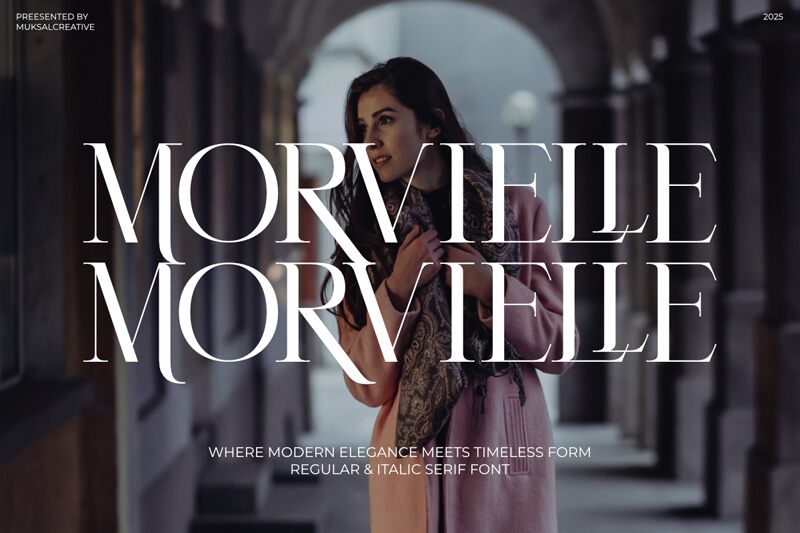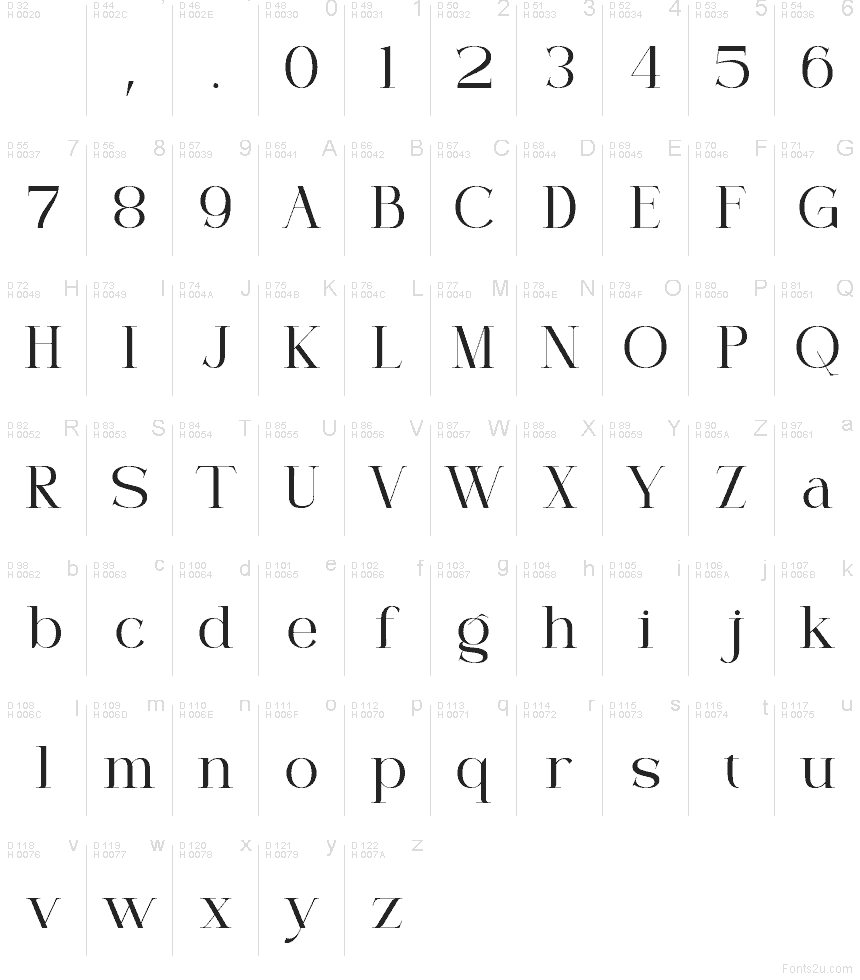
Morvielle Regular
Morvielle od Muksal Creative je bezplatné patkové písmo s vysokým kontrastem, jehož výrazná svislá osa a tenké spoje vytvářejí elegantní, módně laděný rytmus. Široké hlavní tahy se ostře prořezávají proti velmi jemným spojnicím, což písmu dodává čistou a vytříbenou siluetu, nikoli tu stroze knižní.
Díky této dynamice je Morvielle ideální pro butikový branding, obaly kosmetiky, záhlaví časopisů, pozvánky či luxusní grafiku na sociální sítě. Morvielle skvěle vynikne i v jídelních lístcích nebo na obálkách lookbooků, kde jeho štíhlé detaily a vytříbený kontrast pomáhají typografii dodat patřičně exkluzivní tón.